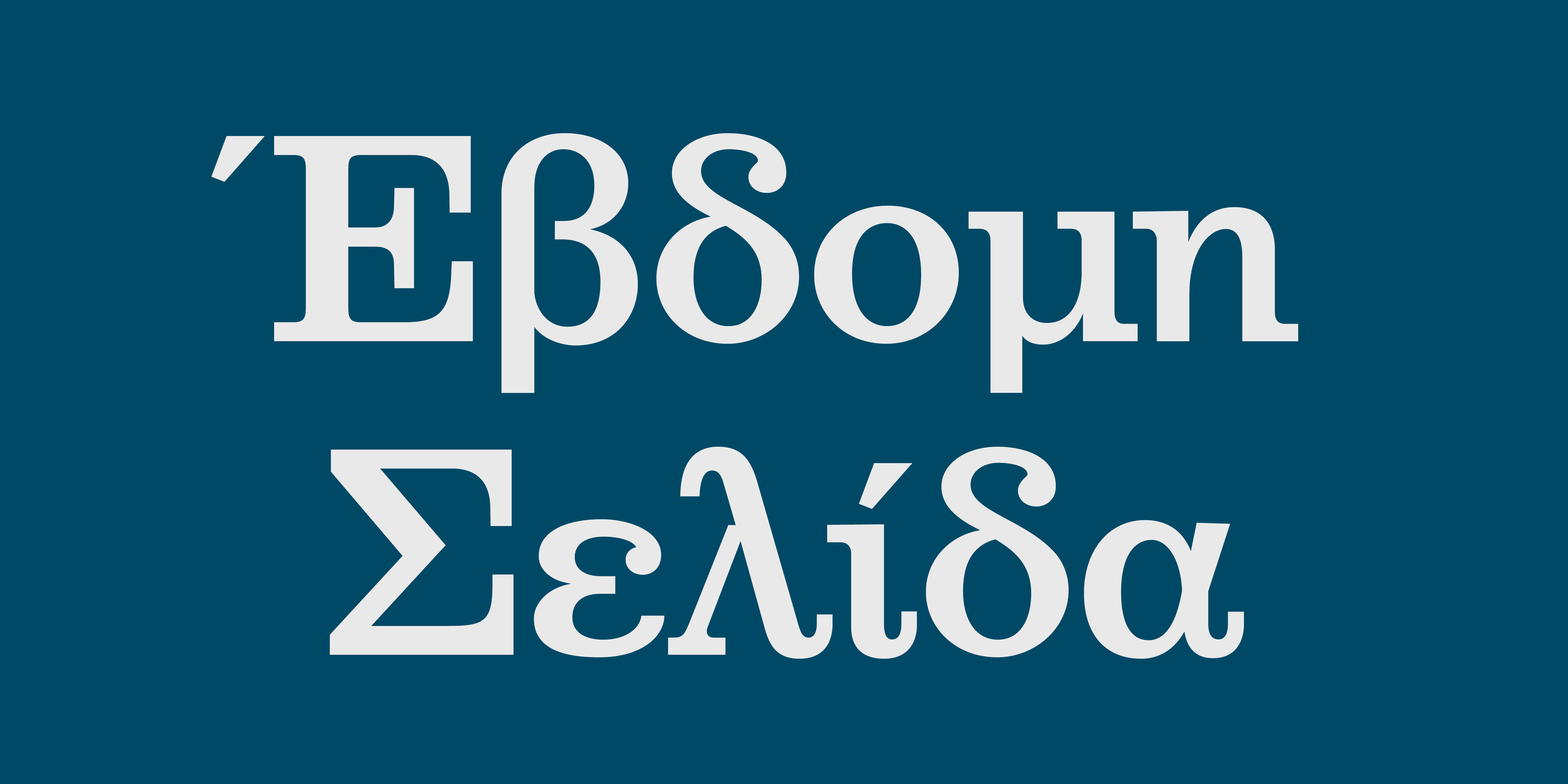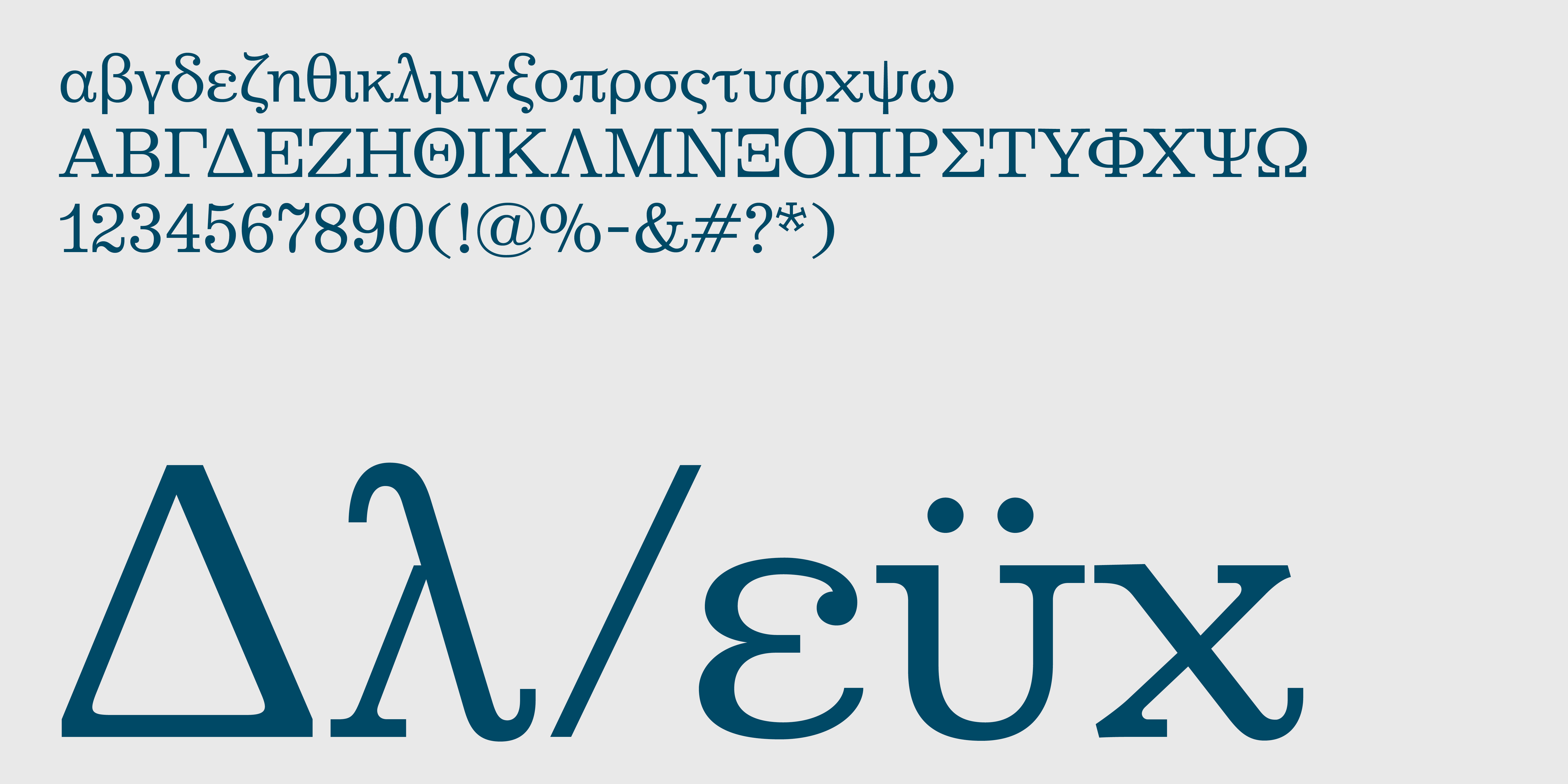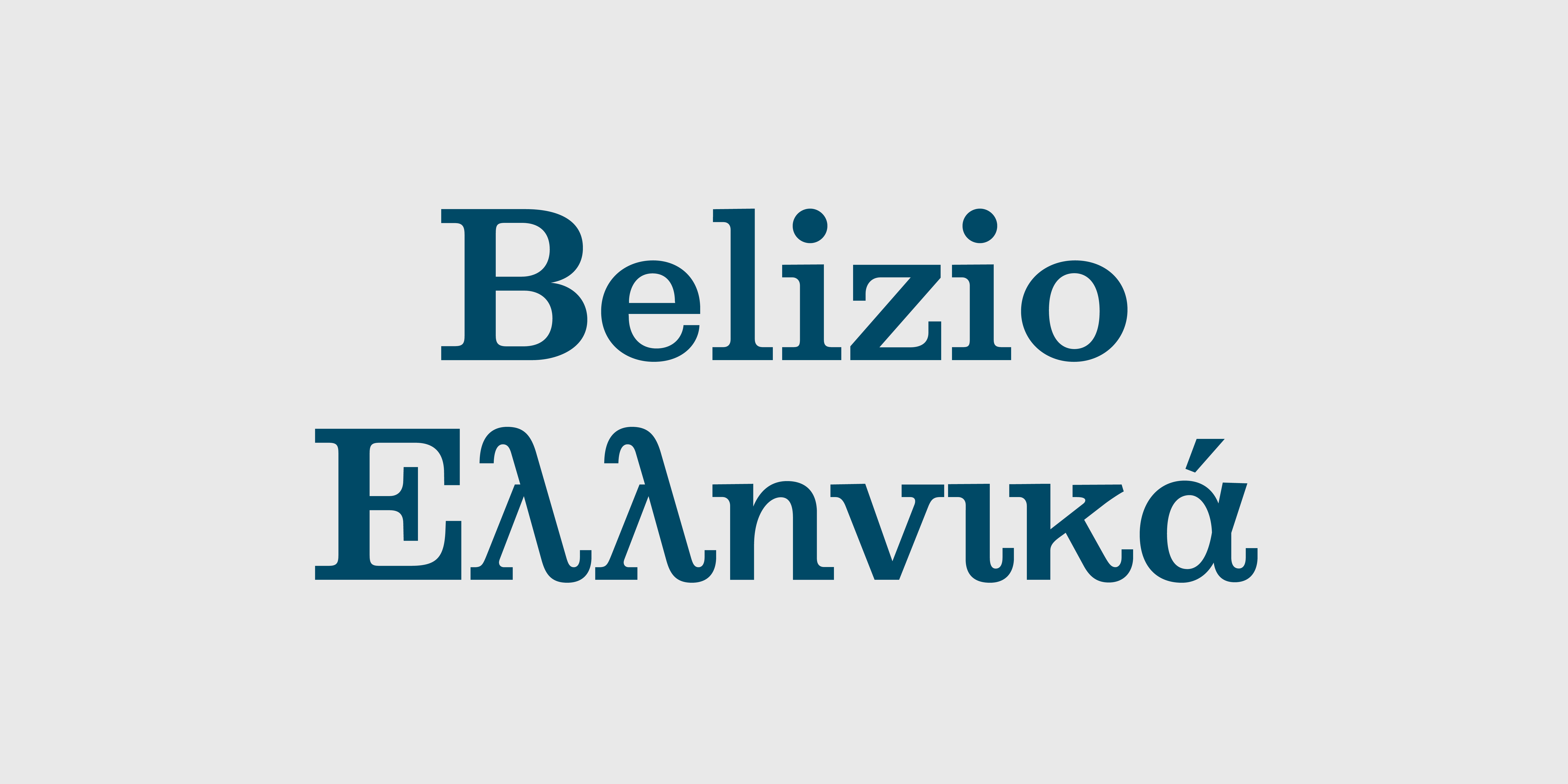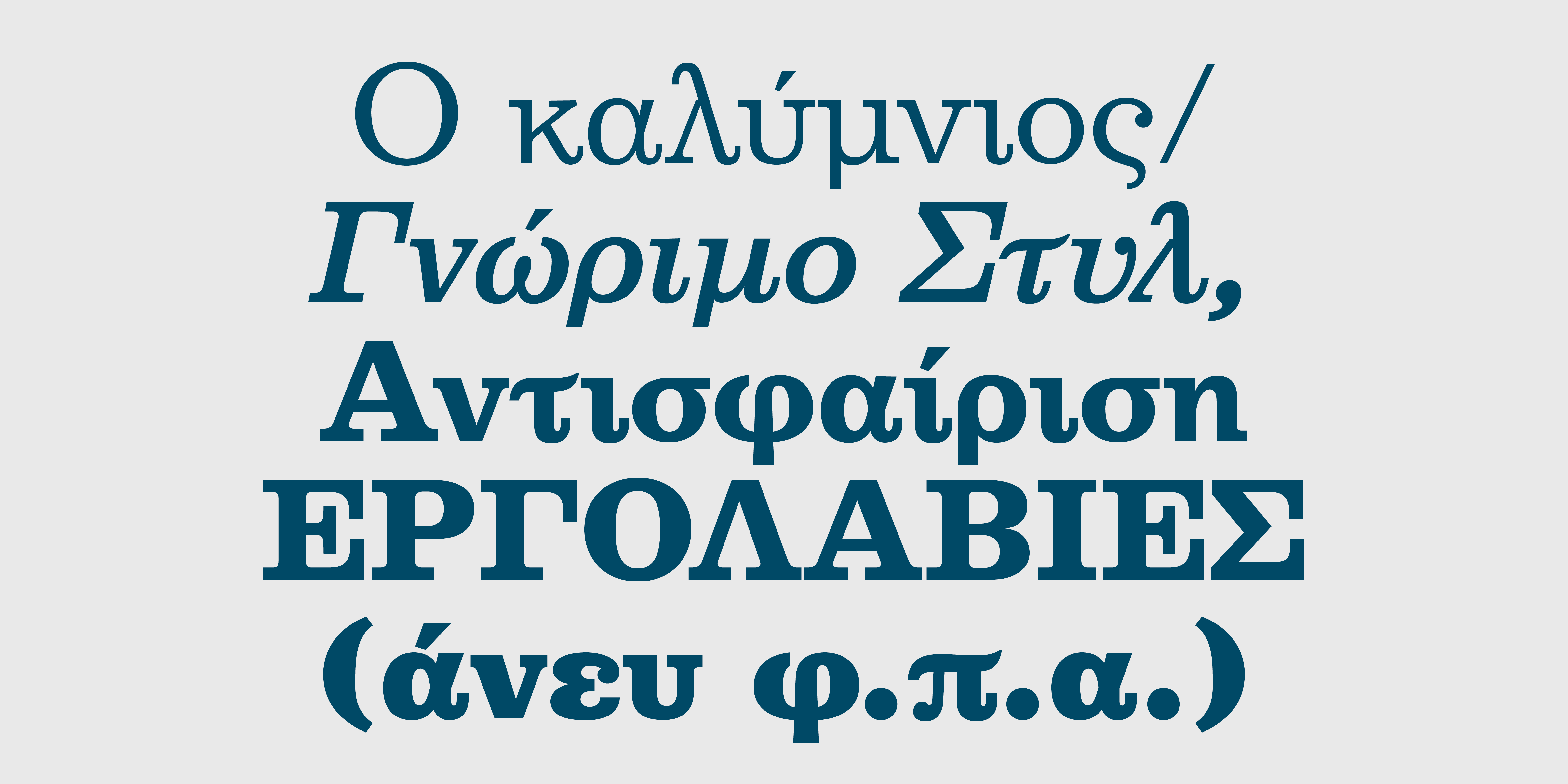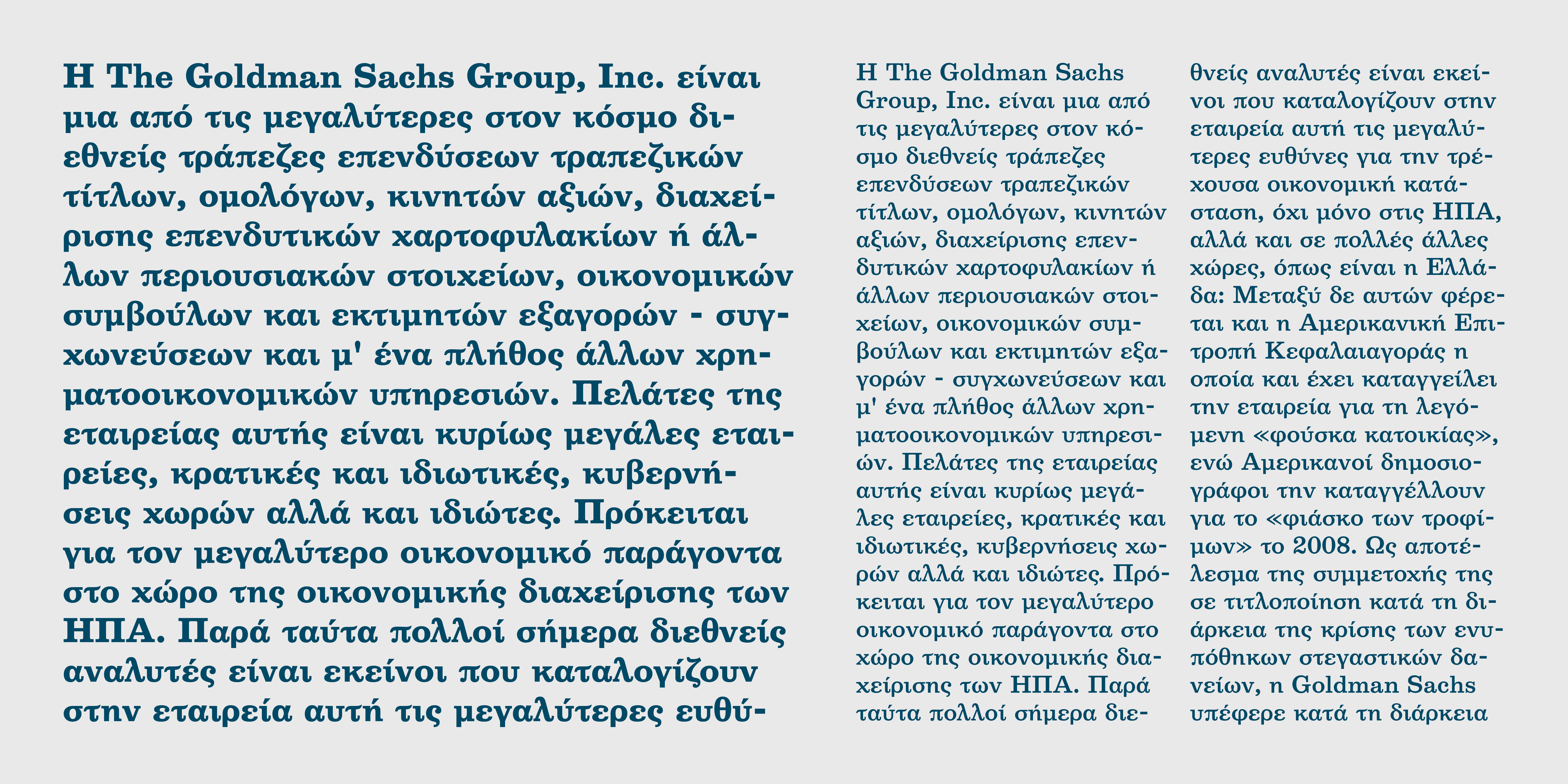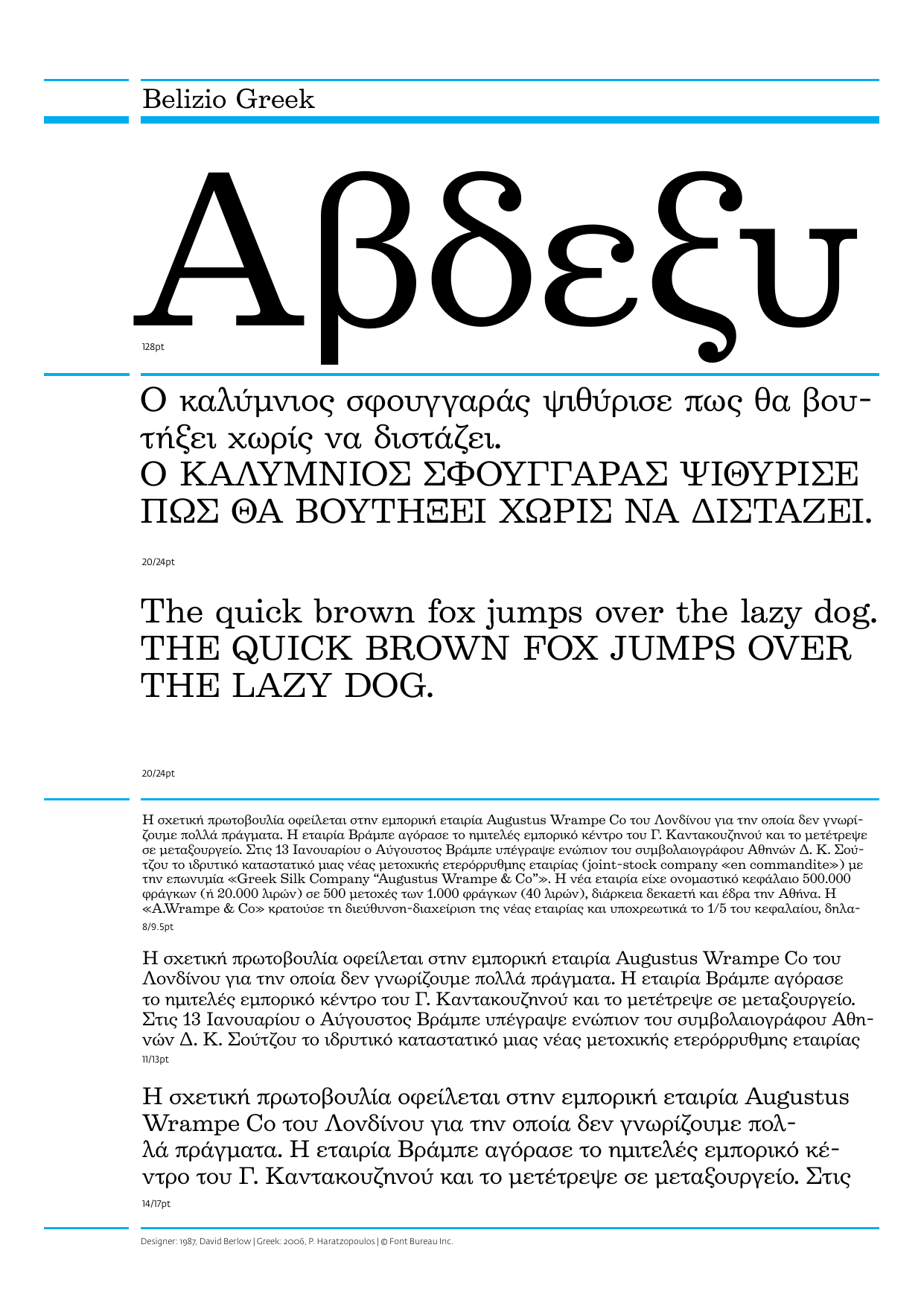
Belizio Ελληνικά
Η Belizio σχεδιάστηκε από τον David Berlow και έχει βασιστεί στην Egizio τη γραμματοσειρά που σχεδίασε ο Aldo Novarese. Το κίνητρο για την εταιρία Nebiolo που ανέθεσε το σχεδιασμό, ήταν να ανταγωνιστεί τη δημοφιλία που είχε εκείνη την εποχή (1955), η γραμματοσειρά Haas Clarendon των Hoffmann και Eidenbenz, ενός άψογου επανασχεδιασμού πάνω στο κλασικό αγγλικό τυπογραφικό πρότυπο. Ο Aldo Novarese, υπήρξε από τους πρώτους σχεδιαστές που μελέτησε και πρότεινε ένα πραγματικό πλάγιο σχέδιο για το ύφος της Clarendon. Ελληνική έκδοση Παναγιώτης Χαρατζόπουλος